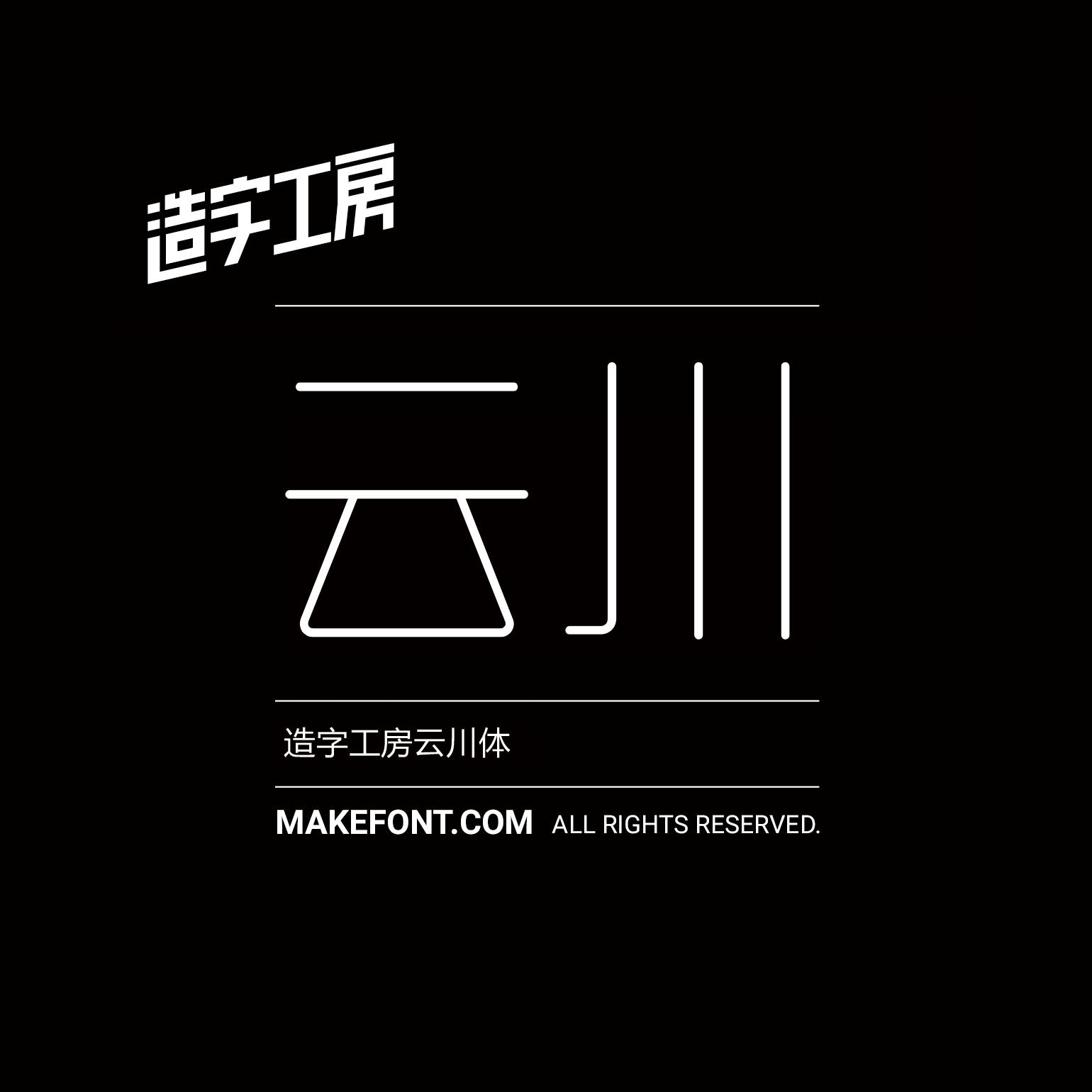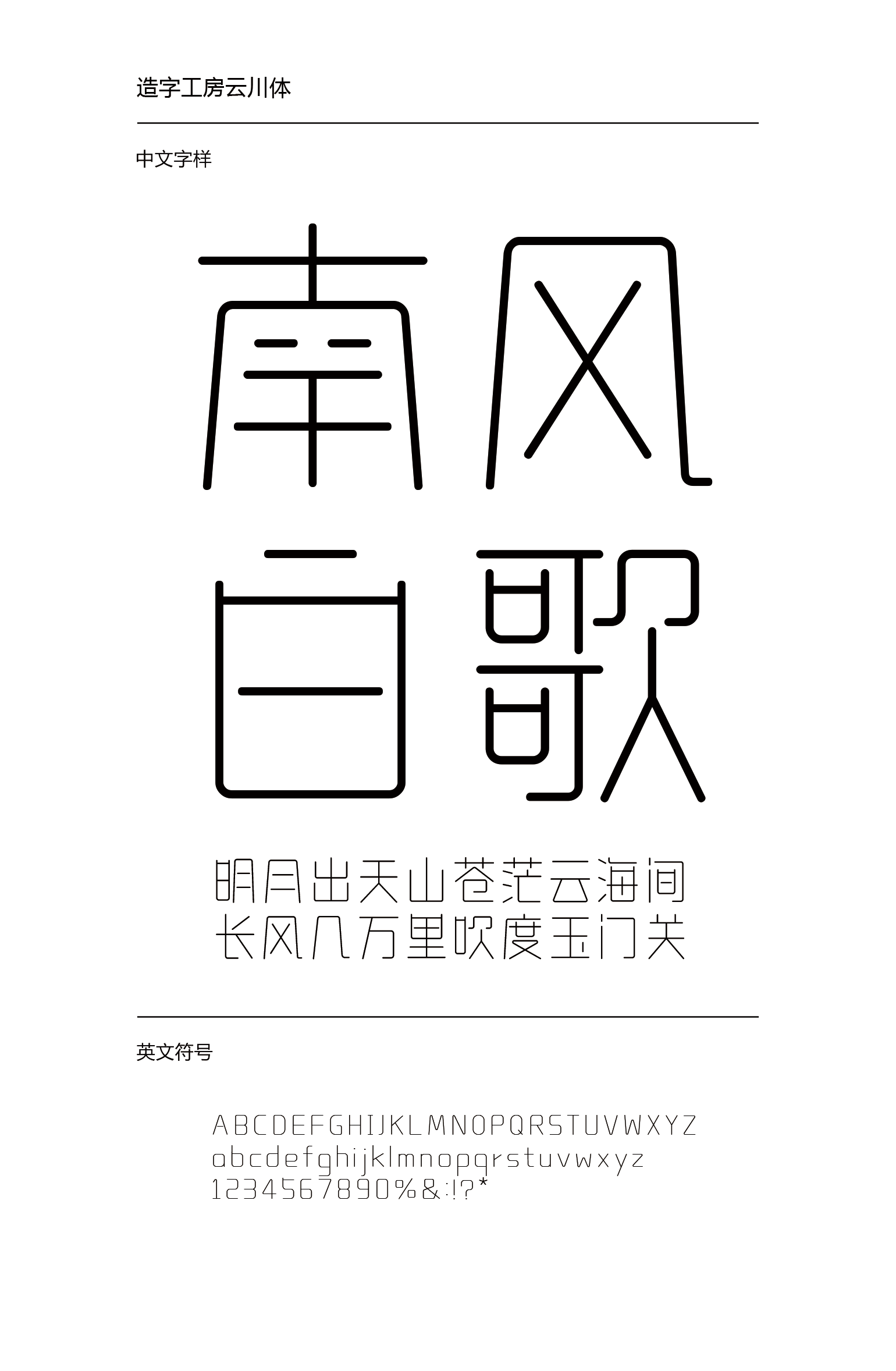
造字工房云川体设计说明
造字工房云川体,笔画纤细舒润,简约洗练,起承转合圆劲均匀,疏密有致。其字形古朴清俊,处处平衡对称、方圆中寓,古风雄健。适用于大标题及个性品牌设计推广等环境。本字体为简体字库,采用OpenType/CID格式,Adobe-GB1-5编码。基于中华人民共和国GB2312-80字符集标准,另按需添加101个汉字。共收容字数6864CJK汉字,ASCII常用字符100个。